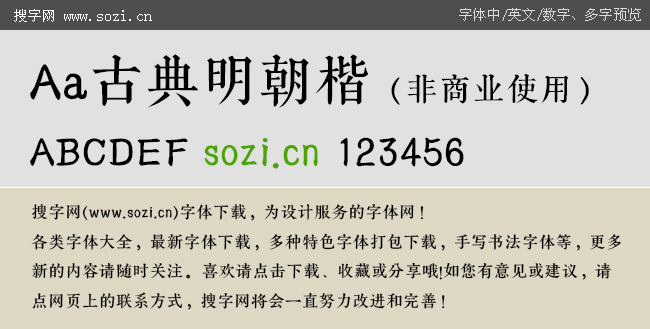
Aa古典明朝楷
搜字網(wǎng)給大家提供一款A(yù)a古典明朝楷(非商業(yè)使用)中文字體下載,Aa古典明朝楷是一款古典字體,該字體筆觸適中,字形端正,視覺(jué)效果非常好。適合應(yīng)用于海報(bào)設(shè)計(jì)、包裝設(shè)計(jì)、網(wǎng)頁(yè)設(shè)計(jì)等應(yīng)用(此字體為個(gè)人非商用版,商用可以聯(lián)系QQ:1006760504)。